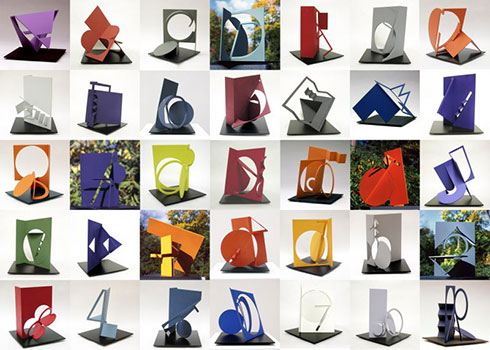
Anlässlich der Schenkung einer Großskulptur an die Stadt Berlin zeigt das Georg-Kolbe-Museum die Werkserie Alphabet des US-amerikanischen Künstlers Fletcher Benton (*1931). Der führende Vertreter des amerikanischen Neokonstruktivismus lebt in San Francisco und hat eine Vielzahl von prominenten Projekten im öffentlichen Raum realisiert. Unter anderem wurde 1993 in Köln die monumentale Skulptur »Triangle Ring« auf dem Barbarossaplatz aufgestellt.
Seit rund 30 Jahren beschäftigt sich Benton mit dem lateinischen Alphabet als plastische Form. Dabei ist stets ein zweidimensionales Quadrat der Ausgangspunkt, aus dem sich durch Schnitte, Biegungen und Knicke die Buchstaben in die Dreidimensionalität entfalten. Die Arbeiten thematisieren die Grenzüberschreitung von der Fläche in den Raum und lassen in der Spannung zwischen Abstraktion und Zeichenhaftigkeit den Prozess der Formfindung nachvollziehbar werden. Die Ausstellung zeigt neben der 35-teiligen »Alphabet«-Serie eine Auswahl von Skulpturen aus anderen Werkphasen Fletcher Bentons.